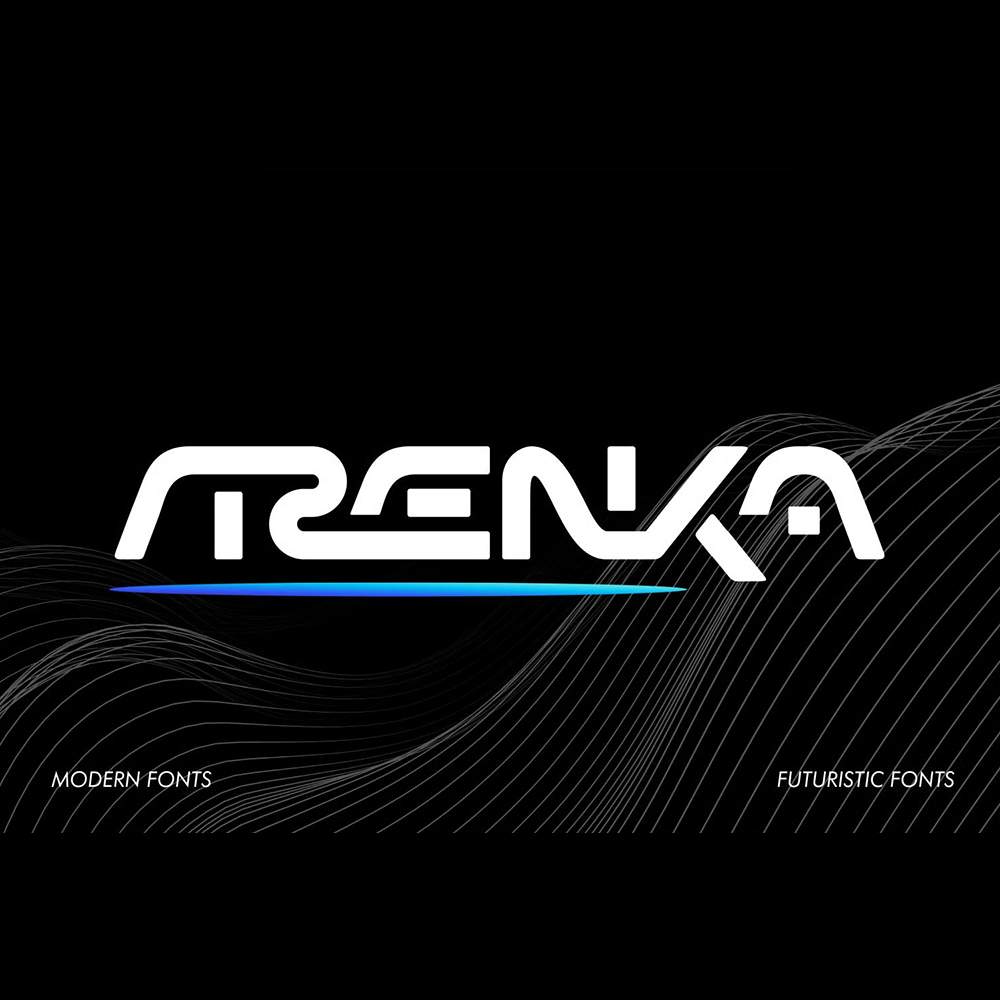
دانلود فونت انگلیسی Arenka Font
فونت پرمیوم و انگلیسی Arenka Font نوآوریهای جدیدی ارائه میدهد و شکلی آیندهنگرانه ارائه میدهد که بسیار مورد توجه است. فونت Arenka به دنبال یادآوری با ترکیب ظرافتهای جدید دوران مدرن امروز است.
مزایای استفاده از فونت لاتین Arenka Font چیست؟